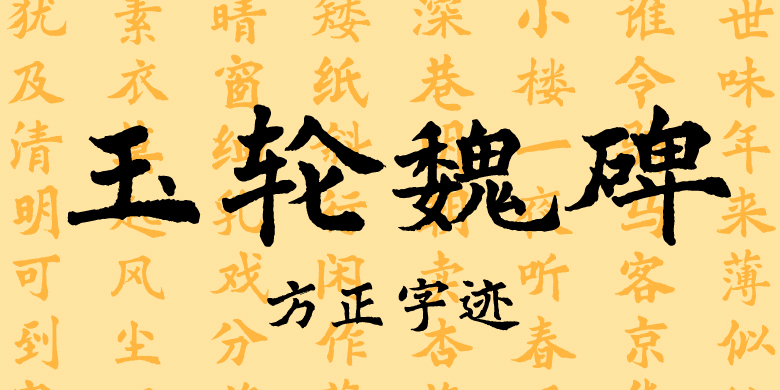
方正字迹-玉轮魏碑
字体品牌: 方正字迹 设计师:陈亚发 字体分类:创意书写、魏碑 字体属性:精品字 字符集:大陆简体(GB2312-80)、简繁扩展(GBK) 发布时间: 2023
魏碑是汉晋时公文所用的文字,史上称之为正书的一种,因而被后人所推崇。但现实的问题是:媒体及市场上所采用的体式单调,书展上出现的又太注重师古,结体与现代结字差距很大。随着时代的发展魏字应在继承传统的基础上体现其快节奏、重灵动、美架构、奇线条的特点,以满足不同客户的需求。